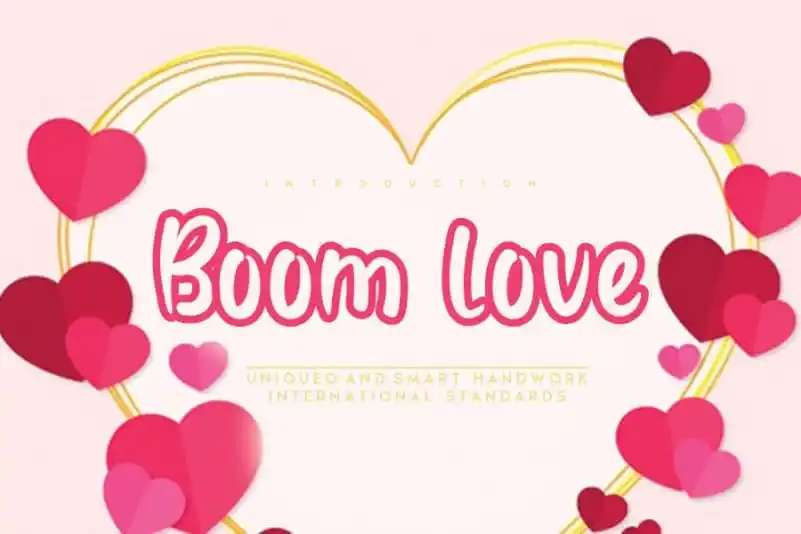
A ‘Boom Love Display Font’ é uma solução elegante para quem busca um estilo atraente na tipografia. Simplificando a elegância à mão livre, ela oferece um único e notável tipo de fonte que mantém seus influentes influências do calligrafismo enquanto se sente contemporâneo e atual. Esta versatilidade atrai uma variedade de ideias criativas, desde cartões-postais e títulos até a estaçãoaria. Este é um adorno perfeito para qualquer projeto gráfico ou design que busque elegância moderna em cada letra. Com sua simplicidade sofisticada, a ‘Boom Love Display Font’ não apenas enriquece seu trabalho com estilo, mas também adiciona personalidade e originalidade.